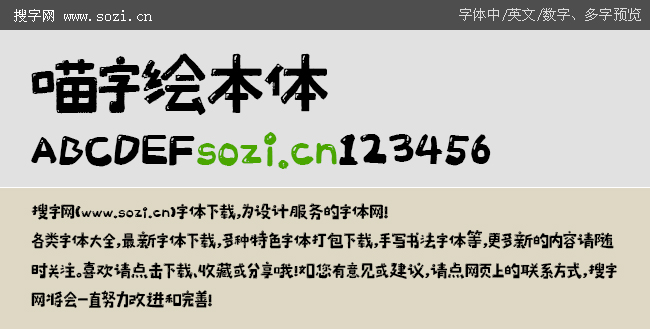
喵字繪本體
搜字網(wǎng)提供一款喵字繪本體中文藝術(shù)字體下載,喵字繪本體是一款卡通風(fēng)格的藝術(shù)字體,喵字海報(bào)體整體錯(cuò)落有致,筆畫(huà)充滿(mǎn)童趣,并帶有高光效果,趣味性十足。此款字體適用于兒童海報(bào)設(shè)計(jì)、卡通包裝設(shè)計(jì)、廣告設(shè)計(jì)等領(lǐng)域。